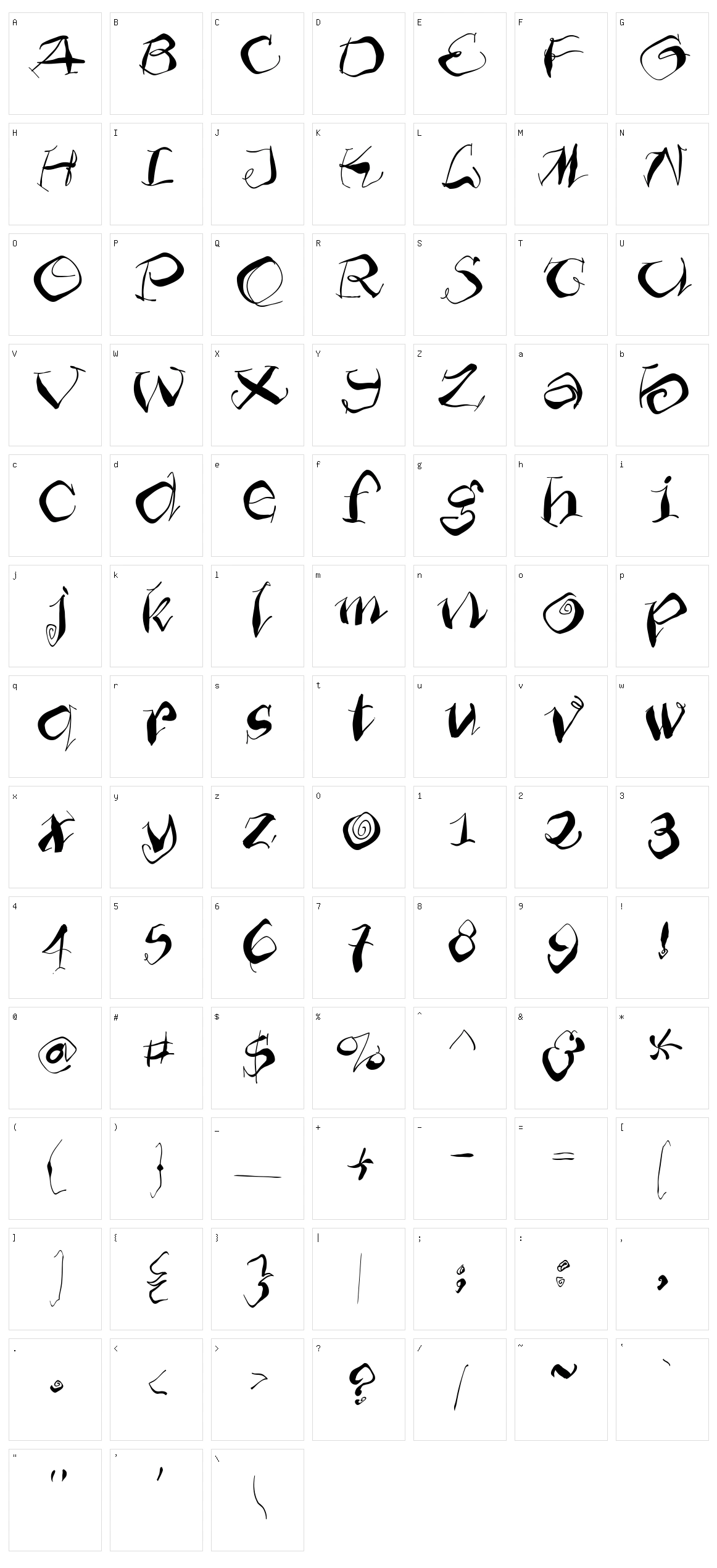
Furioso!
Da war das Vergnügen, eine kalligraphische Marotte, schön zu
schreiben, mit Bedacht die Feder aufs Papier zu setzen, einmal ganz
exzentrisch anders zu besetzen: Kalligraphisch, aber auch
elektronisch, mit Bravour die Buchstaben in den Computer zu bringen,
mit ruppigem Strich. Das geschah mit dem Wacom Stift und Pad, der
direkt mit dem Fontographer von Macromedia gekuppelt ist. Natürlich
kann man damit auch ganz sanfte, liebliche Zeichen erzeugen, wie die
kunstgewerblichen Schönschreiber mit ihrer Sepiatinte. Das ist nur
eine Frage des Temperaments.
There was a certain pleasure to interpret the calligraphic caprice
of fine writing in a completely different and eccentric way:
to digitize the letters with verve, both electronically and
calligraphically. It was done with the Wacom pen and pad connected
directly to Macromedia's Fontographer. Of course it's possible
to generate gentle, charming characters like the professional
calligraphy artists do with sepia ink. It's just a question of
temperament.